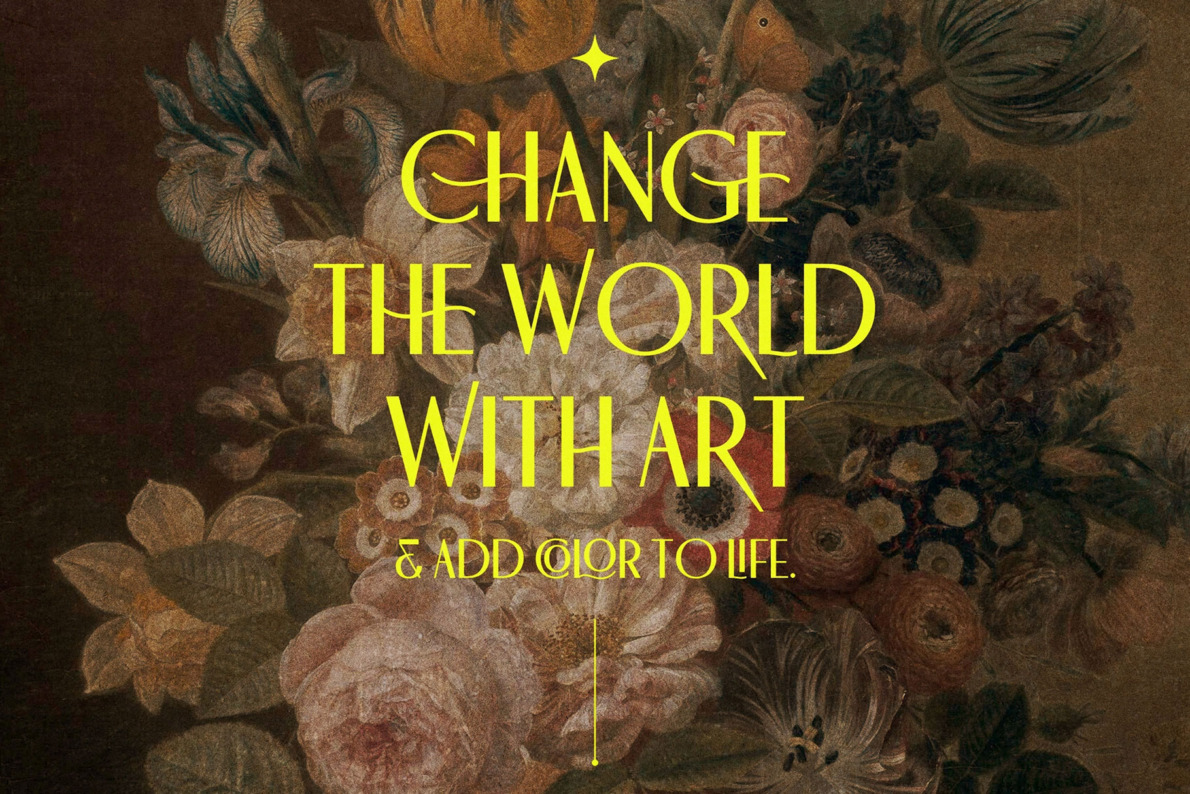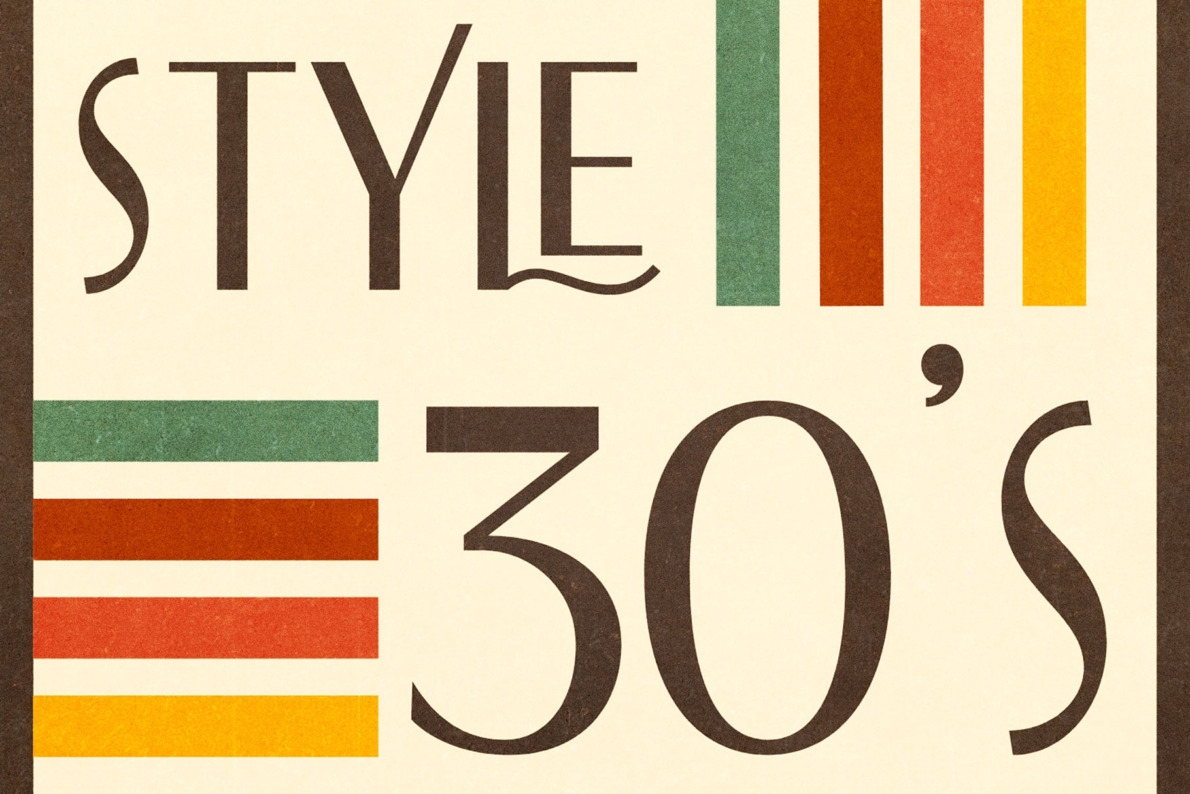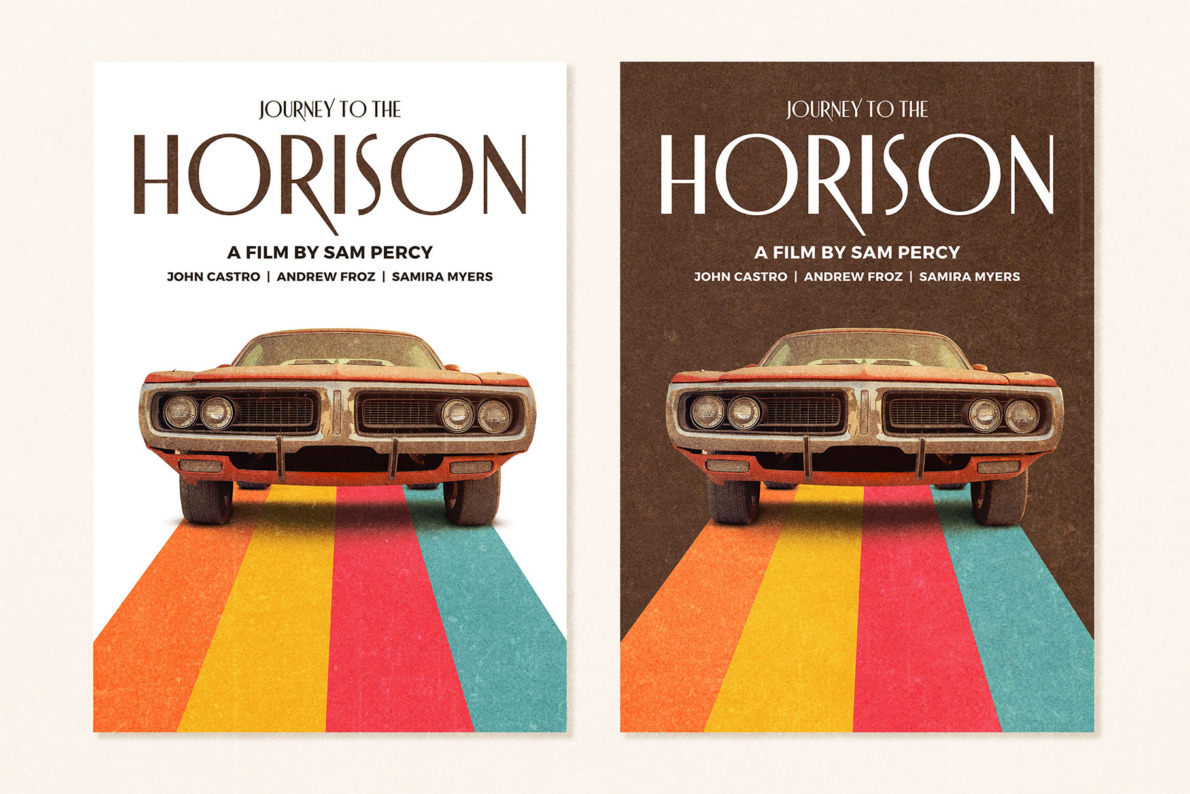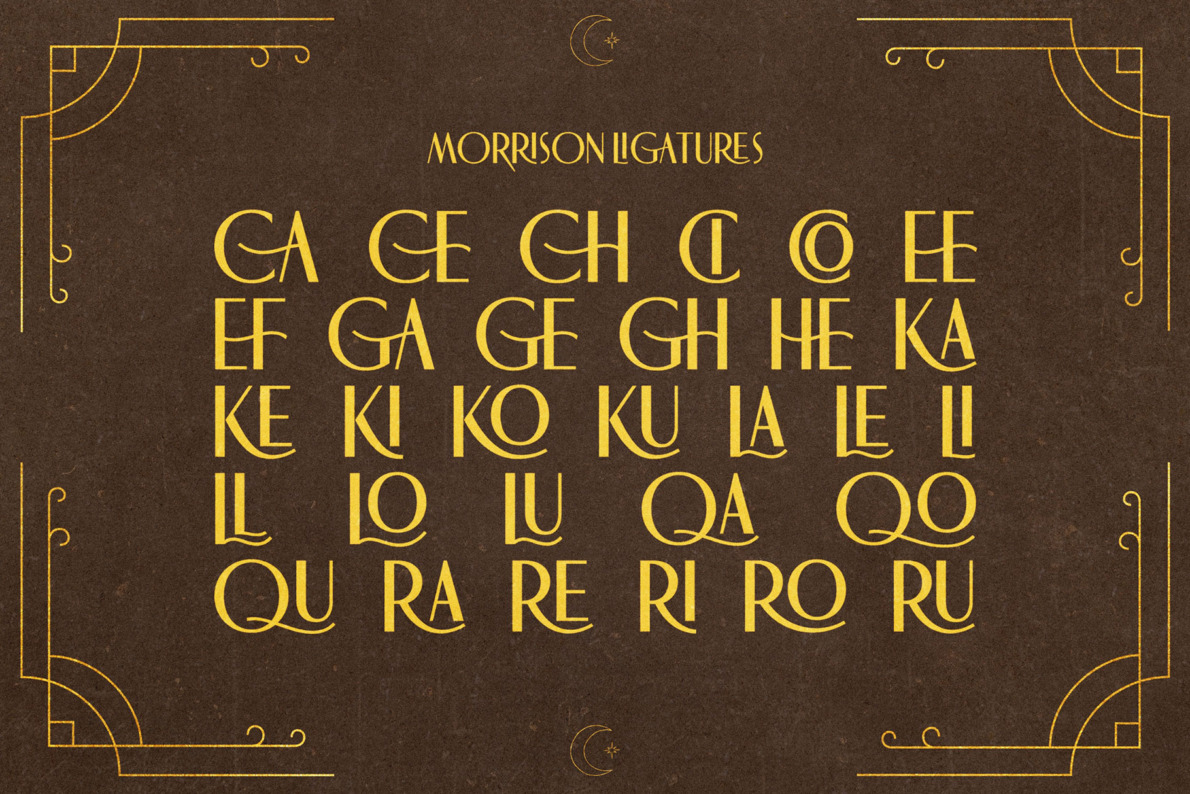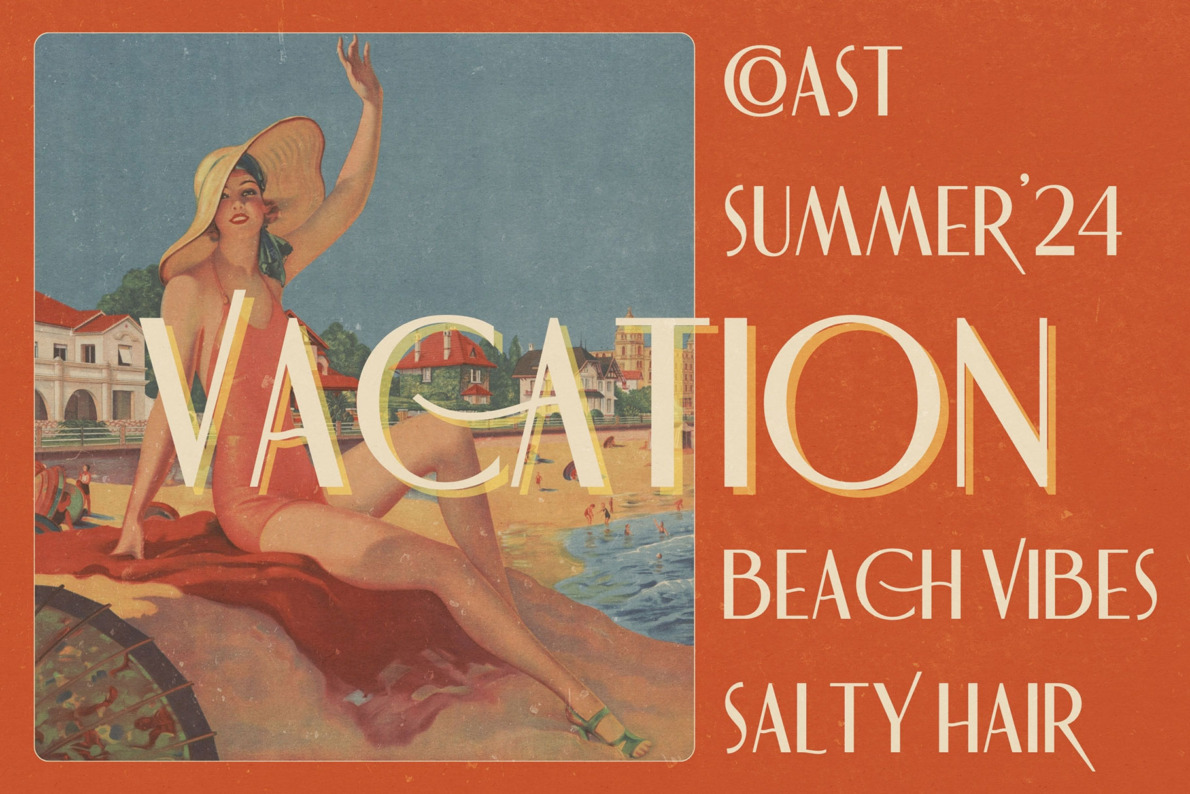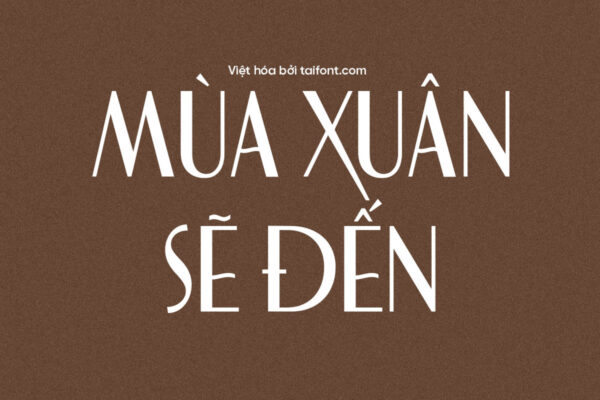
Giới thiệu về Font TF Morrison Việt hóa
TF Morrison Việt hóa là một font chữ không chân (sans-serif) nổi bật với những nét mảnh mai, tinh tế, mang đến vẻ đẹp thanh lịch, cổ điển nhưng vẫn rất hiện đại. Font này gợi cảm giác sang trọng, nhẹ nhàng và đầy phong cách, lý tưởng để tạo nên sự độc đáo và tinh tế cho các thiết kế.
Với sự duyên dáng trong từng đường nét, Morrison là lựa chọn hoàn hảo cho các ấn phẩm cần sự tinh tế, thanh thoát và một chút hoài cổ:
- Thiết kế tạp chí: Hoàn hảo để sử dụng cho nội dung chính, các tiêu đề phụ, hoặc các đoạn trích dẫn trong các tạp chí thời trang, nghệ thuật, kiến trúc, hoặc tạp chí về phong cách sống. Nét mảnh của font giúp tạo không gian thoáng đãng, sang trọng và dễ đọc.
- Thiết kế cổ điển: Phù hợp cho các dự án mang hơi hướng vintage, retro nhưng vẫn giữ được nét hiện đại, chẳng hạn như poster phim cũ, bìa sách văn học kinh điển, hoặc các ấn phẩm kỷ niệm. Morrison giúp tạo không khí chân thực và đầy hoài niệm mà không bị lỗi thời.
- Thiết kế tối giản và cao cấp: Lý tưởng cho các thương hiệu muốn thể hiện sự sang trọng, tinh tế và tối giản trong logo, bao bì sản phẩm hoặc các ấn phẩm truyền thông.
Với TF Morrison Việt hóa, bạn có thể dễ dàng thổi hồn tinh tế, sự thanh lịch và một chút cổ điển vào các thiết kế, tạo ra những sản phẩm không chỉ đẹp mắt mà còn đầy cảm xúc và chiều sâu.
Font Việt hóa TF Morrison